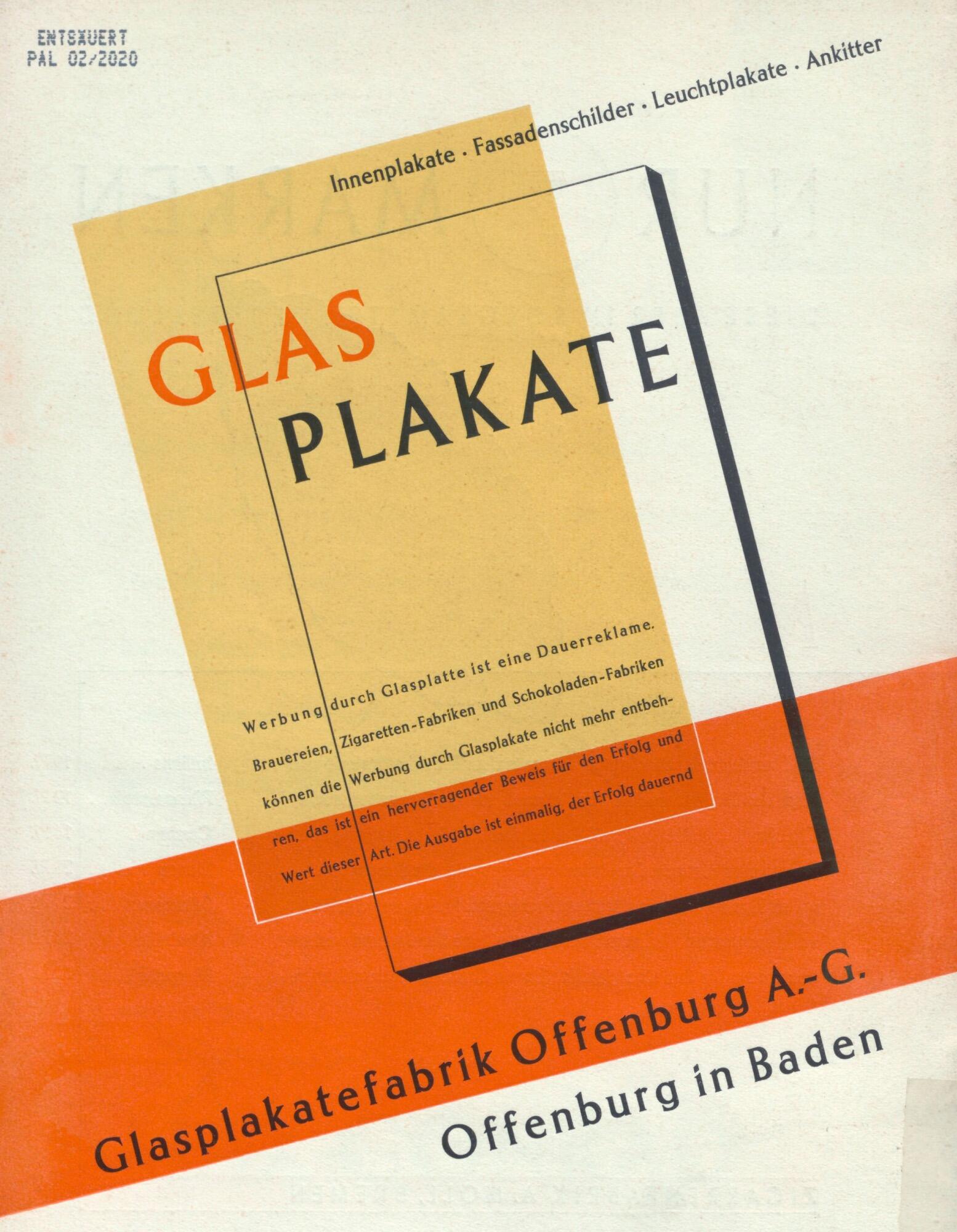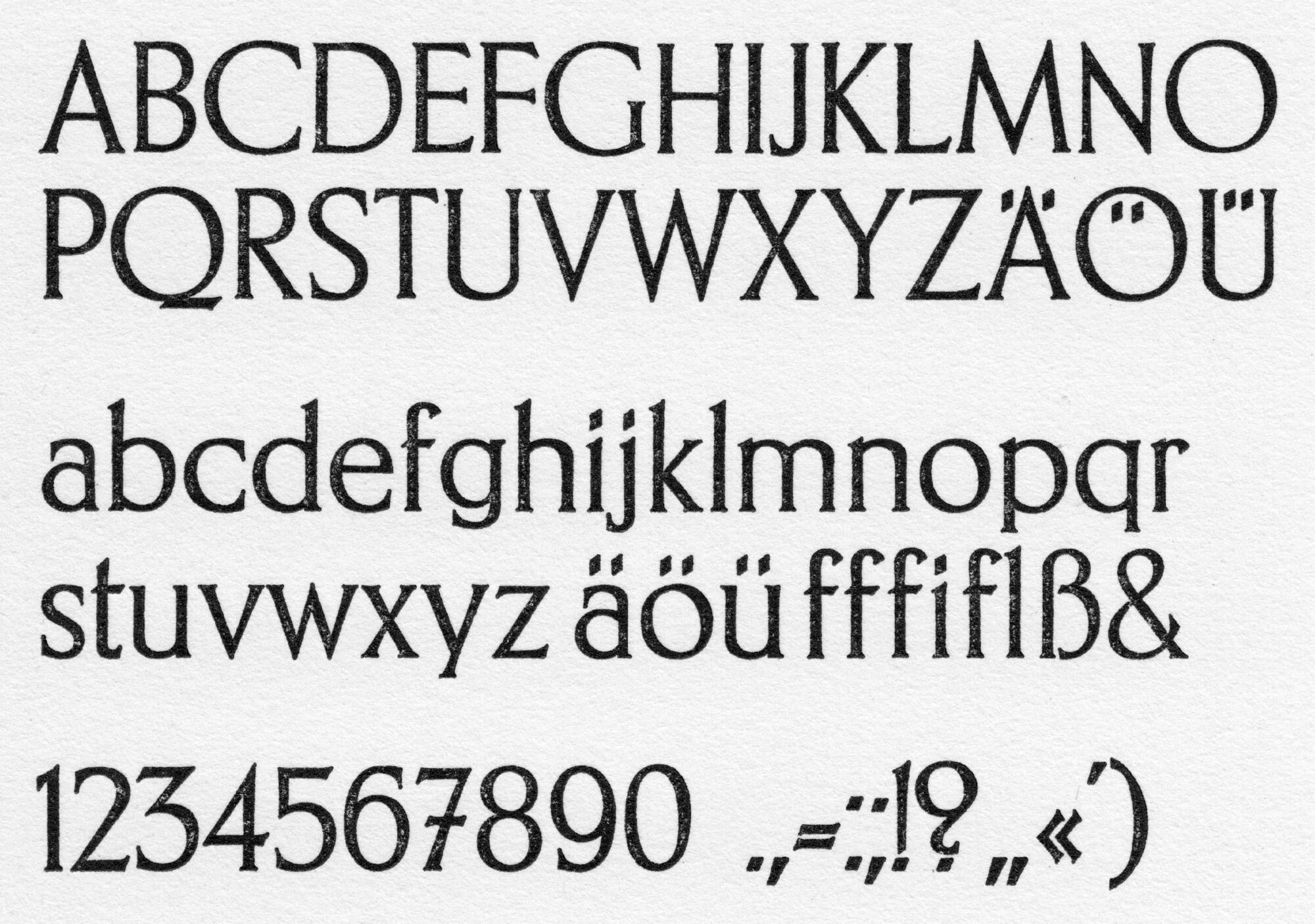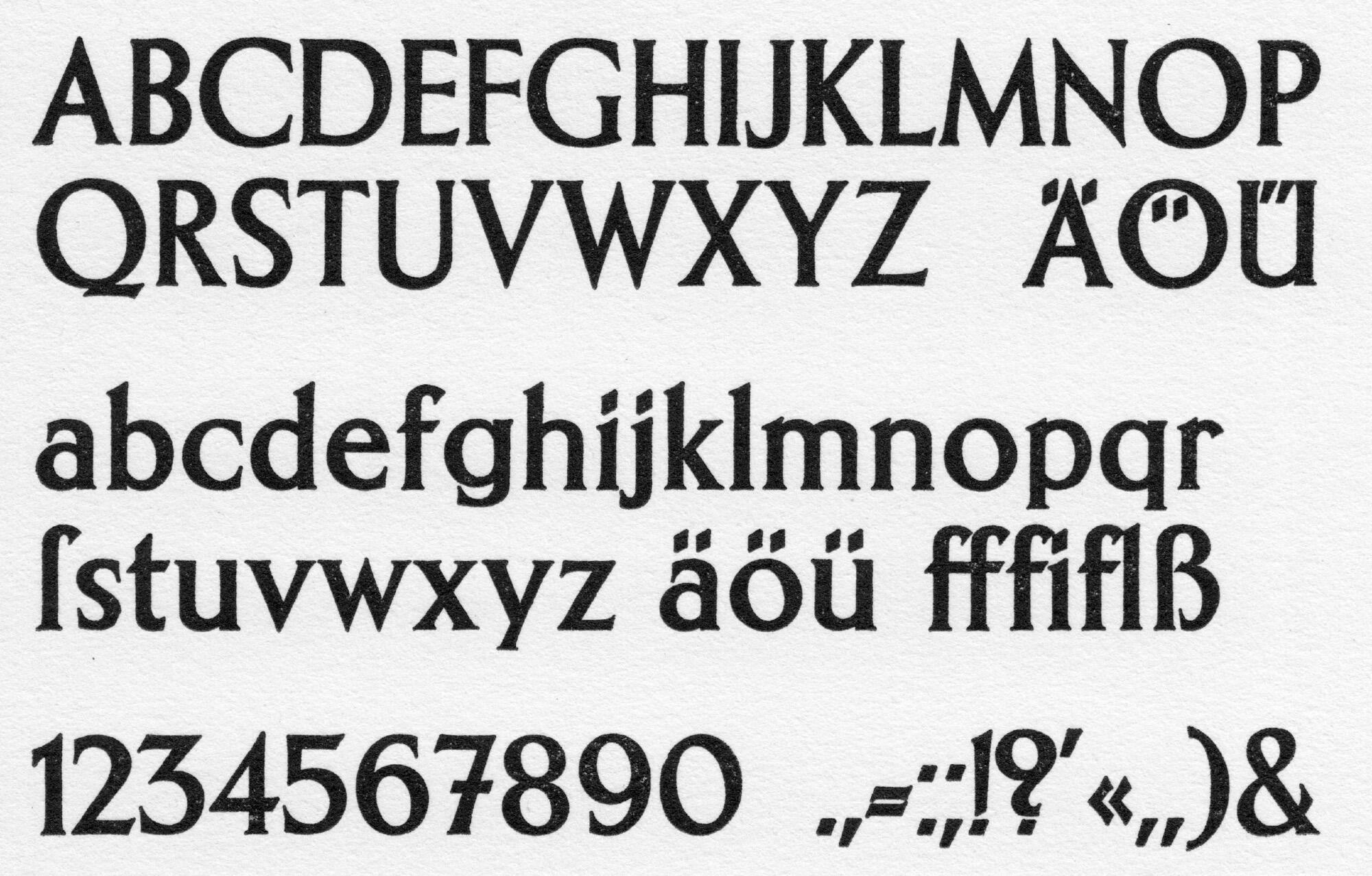
- 1929
- Antiqua humanistisch
Die Mundus-Antiqua ist eine Schrift von Willy Schwerdtner und erschien 1929 bei der D. Stempel AG. Es waren zwei Strichstärken (mager und halbfett) verfügbar, jedoch keine Kursive. Erhältlich waren jedoch separate Schaugrößen-Versalien.
Digitalisierungen sind nicht bekannt.
Beschreibung aus einen Original-Muster der D. Stempel AG: Die moderne Schrift die einen Fortschritt in der Typographie bedeutet und die die Entwicklung weiterführt. Die Mundus-Antiqua ist die Verwirklichung eines Gedankens, der für die Typographie gesunde Entwicklung bedeutet. Sie ist eine auf klassischer Grundlage dem Formgefühl unserer Zeit gemäß gestaltete Type. Das ist ihr Grundzug und darin beruhen ihr Vorzug und ihre Möglichkeiten für die Übernahme der Rolle, die wir ihr zugedacht haben. Sie hat nämlich bereits eine Geschichte, diese Schrift. Ihre Entstehung ist nicht Sache des Zufalls gewesen, sondern wir sind in Erkenntnis der in der Zeit liegenden Notwendigkeiten planmäßig auf die Schaffung dieser Schrift als Typus ausgegangen. Die Mundus-Antiqua ist das Ergebnis eines Wettbewerbs, zu dem wir eine Reihe namhafter Schriftkünstler eingeladen und als dessen Aufgabe wir den Entwurf einer Schrift, die »unserer Auffassung nach eine Synthese klassischer Druckschriftformen mit dem in neuzeitlichen Gestaltungen auf den verschiedensten Gebieten sich ausdrückenden Formwillen darstellen müßte«, aufstellt hatten. Unsere Schriftidee hat sich auf Grund einer Zeichnung von W. Schwerdtner, Berlin, dem Schöpfer unserer vom Werbewesen aller Kulturländer günstig aufgenommenen Metropolis-Schriftenreihe, verwirklichen lassen. Mit der Mundus-Antiqua sollte eine über die Grotesk hinaus weiter führende Richtung eingeschlagen und heutigem Stilwillen ein neuer Ausdruck gegeben werden. Außerdem liegt ihrer Schaffung der Gedanke einer in aller Welt und zu Drucken für alle Welt brauchbaren modernen Weltletter zu Grunde. Ihre Formensprache wird überall in der Welt verstanden. Sie ist schön und edel, sie wirkt neuartig und frisch; Kraft, Leben und Bewegung sind in ihr. Anzeigen und Werbedrucken sichert sie Eigenart, Anziehungskraft und eine weltmännisch-moderne Haltung.